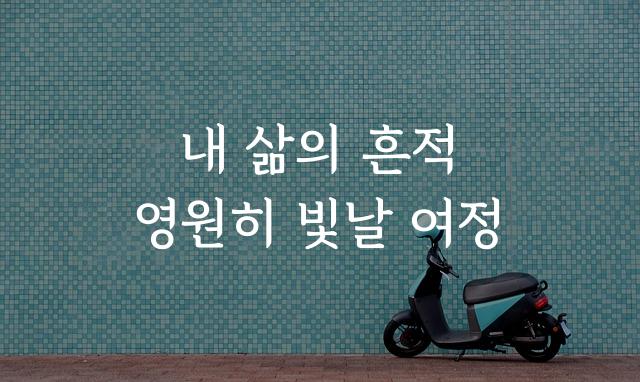
경기천년제목은 경기도청에서 제작한 제목용 폰트로, 둥근 고딕의 부드러운 곡선과 장식적인 요소가 특징입니다. 이 폰트는 현대적 감각과 전통적 아름다움을 조화롭게 담아내어 다양한 디자인에 활용될 수 있습니다.
경기천년제목은(는)
별모양/패턴, 길고/크고, 기본 고딕, 복실복실, 부드러움, 감성적인, 장식 스타일, 둥근 스타일 계열의 생김새를 가지고 있으며
웹/앱 디자인, 출판물 제목, 출판 디자인 등에서 자주 활용되며, 효과적인 메시지 전달에 적합합니다.
이 폰트는 출판/미디어, 문화/예술, 건축/인테리어 분야에 잘 어울리며,
클래식한, 고급스러운, 전문적인 느낌을 담고 있는 것이 특징입니다.